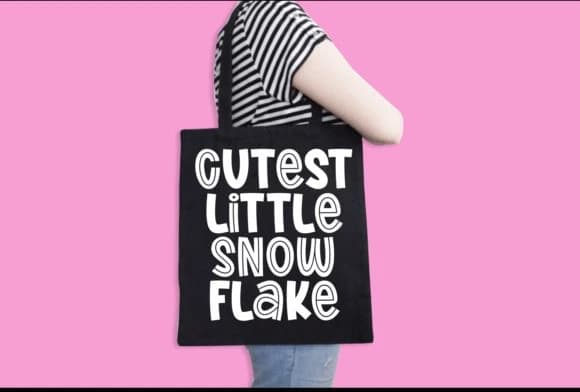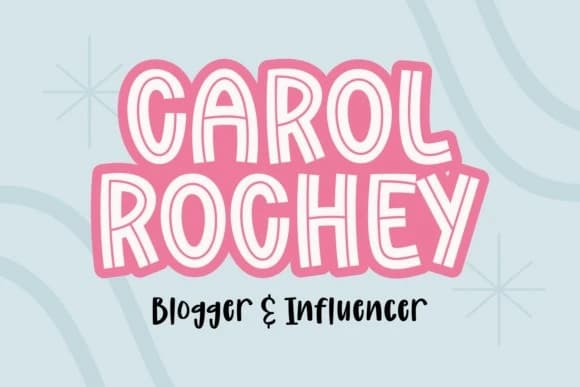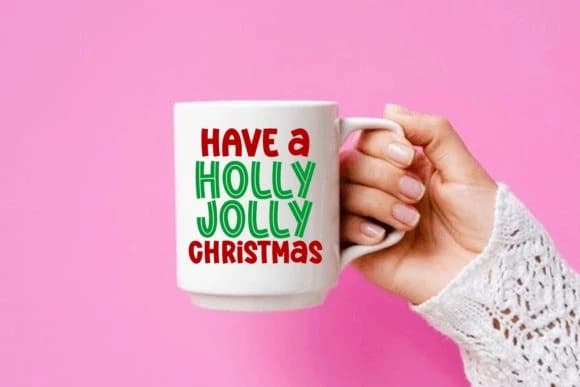
Skylight Candy Yazı Tipi
Skylight Candy Font, herhangi bir projeye oyunbaz ve canlı bir çekicilik katan bir yazı tipidir. Genç ve neşeli bir ruhu yakalamayı hedefleyen projeler için mükemmel olan Skylight Candy, tasarımlarınıza hoş bir tatlılık katıyor.
Skylight Candy Font, herhangi bir projeye oyunbaz bir çekicilik dokunuşu katan neşeli ve canlı bir fonttur. Genç ve neşeli bir ruhu yakalamayı hedefleyen projeler için mükemmel olan Skylight Candy, tasarımlarınıza hoş bir tatlılık katıyor.